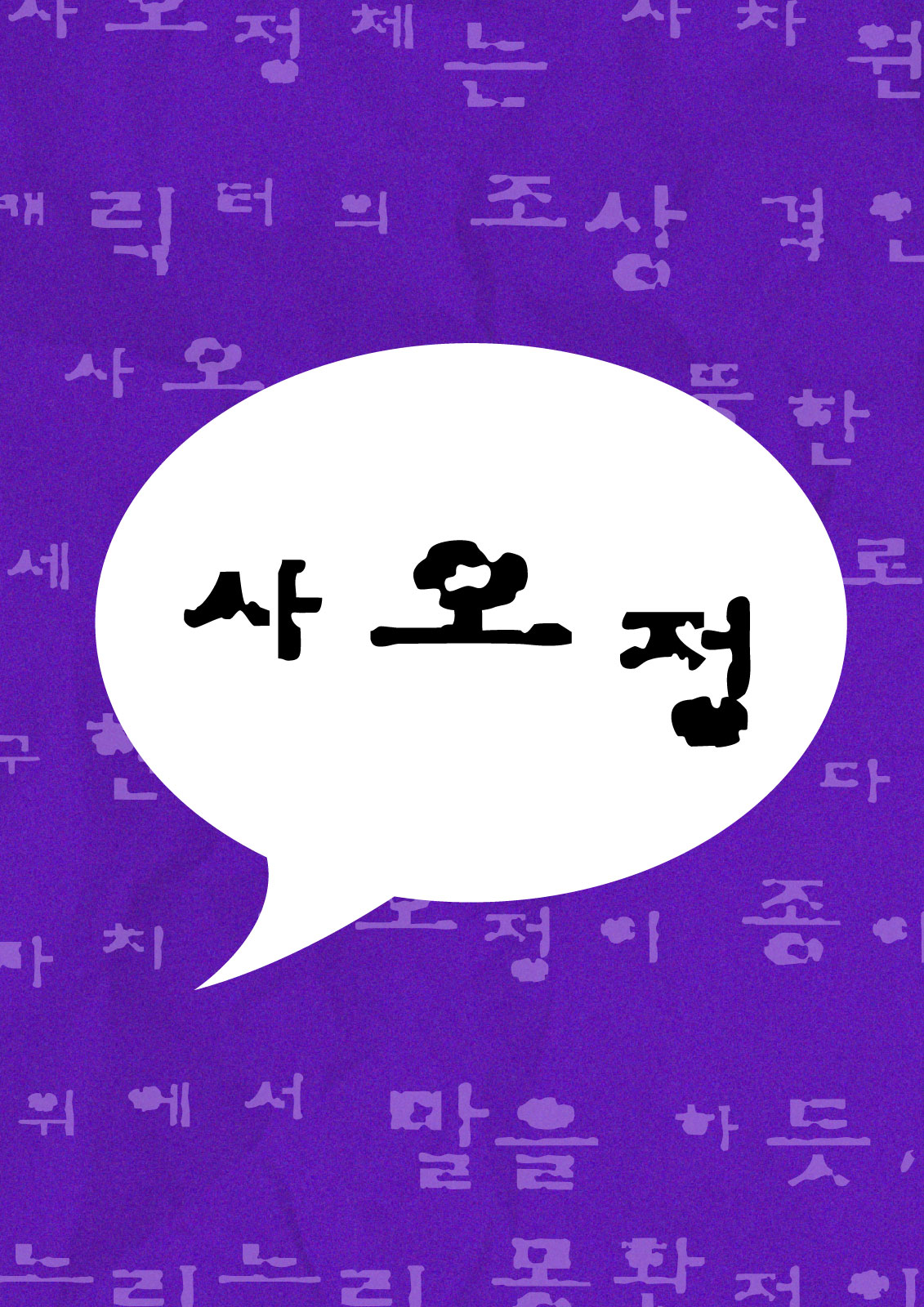
사오정
Yoon 사오정
사오정체는 사차원 캐릭터의 조상 격인 사오정의 엉뚱한 세계를 시각적으로 구현한 폰트입니다. 마치 사오정이 종이 위에서 말을 하듯, 느릿느릿 몽환적인 리듬감이 기묘한 기분을 선사하지요. 어쩐지 엉뚱한 이야기를 하고 싶을 때, 사오정 폰트와 함께하세요.